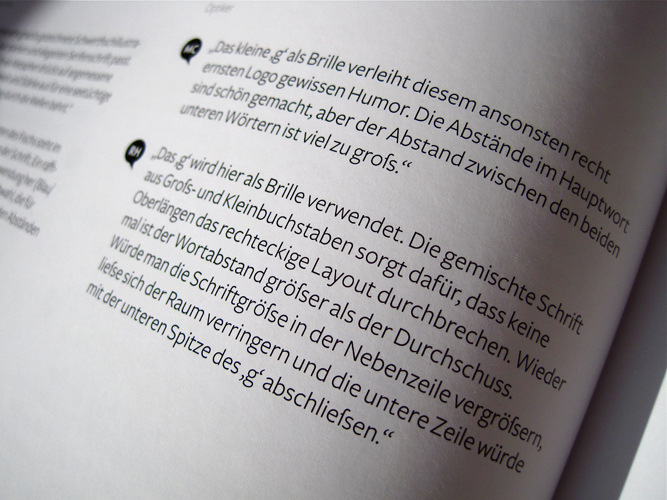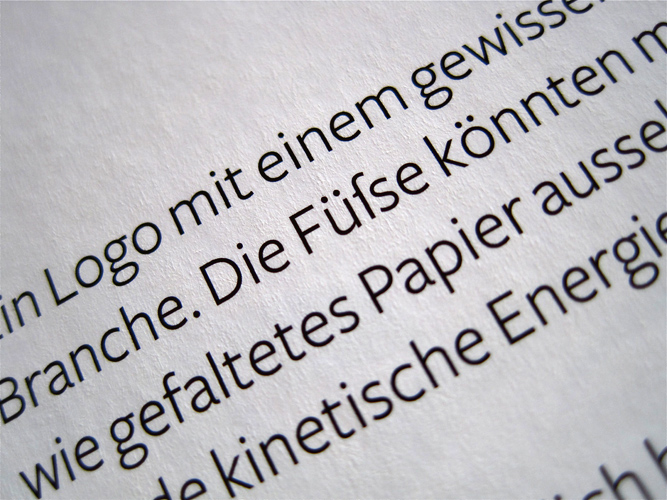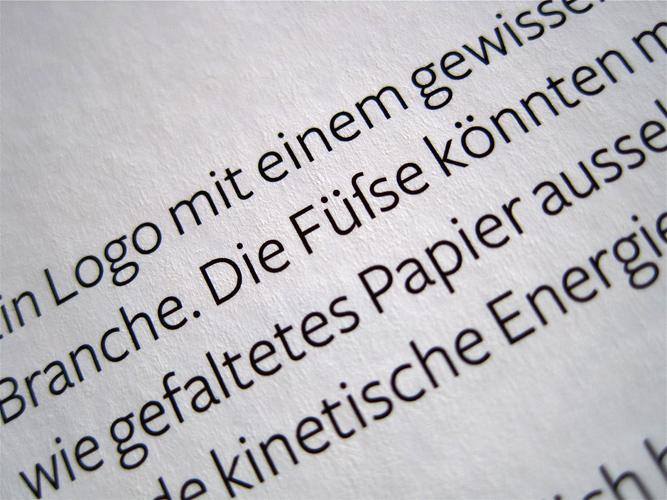
Dieses Buch treibt mich in den Wahnsinn!
Jedes Mal, wenn ich dieses Buch in die Hand nehme, bekomme ich schlechte Laune*! Und es wird nicht besser. Ich habe das Buch schon lange, allein: An dieses ß-Konstrukt gewöhne ich mich nicht. Ich stolpere darüber, bei jeder einzelnen Anwendung. Ich verlese mich, es ärgert mich. Wenn Typografie der Dienst am Leser ist, dann hat das Buch diesen Zweck nicht erfüllt. :grummel:  :bandit:
Geht es Euch auch so oder pflege ich da eine Einzelantipathie?
* Und das liegt nicht nur an den mitunter schwer erträglichen Plattitüden, die die bewertenden Gestalter da vom Stapel lassen. Und dem inflationär verwendeten Begriff »konzeptuell«. Und dazu die teilweise sehr seltsamen Bewertungen … Auch lassen mich einige merkwürdige Formulierungen vermuten, dass die Übersetzung der englischen Originaltexte an manchen Stellen nicht ganz gelungen ist …
Sagen wir mal so: Wenn die ß-resistenten Schweizer das verzapft hätten, könnte man sagen: Besser als ss ist es allemal, also ein kleiner Schritt in die richtige Richtung. Wenn das aber, wie zu argwöhnen ist, als ß-Substitut gedacht ist, dann ist es einfach unerträglich und Deine schlechte Laune ist berechtigt.
Jessasmariundjosef, da steht derart überhebliches Geschwurbel drin, dass ich gar nicht weiter reinschauen möchte. Margo Chase hat sich mit ihrer "erste Wahl" und den Aussagen zur Nicht-Berücksichtigung der Reproduktion so derart selbst ins Knie geschossen, dass ich das nicht wirklich ernst nehmen kann.
Ma abgesehen von der Möchtegern-Schrift: Schaut her, wie toll ich bin.
Ja bertel, Du hast vollkommen recht! Die Kommentare, die dort zu den Logos stehen, sind zwar in manchen Fällen interessant, in vielen Fällen aber bloße Beschreibungen dessen, was man ohnehin sieht und in überraschend vielen Fällen sind die Kommentare inhaltlich sehr oberflächlich und kurz gedacht (oder auch gar nicht mal so schlau). Bei etlichen ausgelobten Favoriten habe ich mir wirklich die Augen gerieben und mich gefragt, ob die Differenz in der Wahrnehmung rein vom unterschiedlichen kulturellen Hintergrund herrührt, oder wie das zustande kommt. Es kann natürlich auch sein, dass ich eine völlig falsche Wahrnehmung habe und die vier Kommentatoren im Buch recht haben ;-).
Aber gerade Margo Chase scheint eine immense Vorliebe für handgezeichnete Logos zu haben und klopft die Entwürfe fast nur darauf ab: handgezeichnet - gut, alles andere - nicht so gut. Erstaunlich ist auch, wie unterschiedlich die Vier den Versalienausgleich und andere Details in den Logos bewerten. Das hat schon einen gewissen Unterhaltungswert und man sieht zumindest, dass anderswo auch nur mit Wasser gekocht wird. Aber ich glaube, wenn das Buch wirklich ein fachlich versierter Ratgeber in der Bewertung von Logos sein möchte, der Anfängern (und Fortgeschrittenen) die sorgfältige und durchdachte Gestaltung von Logos nahebringen soll, dann wäre es sinnvoller gewesen, vorab einige Qualitätsmerkmale und Bewertungsparameter zu definieren, anhand derer die Betrachter die Logos dann einordnen, als diese eitle Dampfplauderei abzudrucken. Klar, ich weiß schon, dass solche Buchkonzepte immer heikel sind und es ist auch immer einfach, sich nachträglich hinzustellen und die Aussagen anderer zu bemängeln. Andererseits kostet das Buch ein ganze Menge Geld und beansprucht für sich, »wirklich gute Logos zu erklären«. Und daran müssen sich die Autoren dann auch messen lassen. Und dann noch dieses »fs« … :-|
PS: Dabei gefällt mir die Schrift ansonsten gut. Und wenn sie sogar ein brauchbares ß enthält, dann ärgert mich der Buchstabenhumbug umso mehr!
Ungewohnt? Ja. Aber es scheint eine Tradition der Setzer zu geben, die das ß für eine Lang-s/s-Ligatur halten, habe schon häufiger solcherlei Bücher gelesen, die aber vor 1900 gedruckt wurden. Nach ein paar Seiten gewöhnt man sich daran schon. Was aber besonders irritierend ist, ist der Nichtgebrauch des Lang-s. Wenn man sich schon derlei Traditionen bedient, sollte man das auch konsequent machen.
Jenseits allem finde ich die Schrift, öh, luftig und wenn das Lang-s benutzt würde, vielleicht sogar spannend.
Gut möglich, dass das eine alte Tradition ist. Ich habe es aber wirklich nicht geschafft, mich daran zu gewöhnen. Ich habe das Buch so gut wie durchgelesen - und es macht mich nach wie vor irre. Ich verstehe nicht, warum man in diesem Buch ohne Not (Stefan schreibt ja, dass diese Schrift über ein reguläres ß verfügt) eine solche Lesestolperfalle eingebaut hat. Ich empfinde das als reine Eitelkeit des Buchgestalters - und mehr als überflüssig.
Wenn dan mal wenigstens das ſs an den Stellen verwendet woirden wäre, wo es hin passt, also z.B. bei daſs und anderen Worten, die auf ss enden, sonst hätte man oft besser zu ſſ gegriffen, und auch sonst ſ regelgerecht verwendet, das wär doch mal was, statt als ſs Ersatz für ß. Auch könnte dies bei Worten wie Fluſsſchifffahrt sogar sehr nützlich sein. in meinen Schriften ist daher auch ſs als Ligatur enthalten, aber eben nicht als ß-Alternative.
Aber es scheint eine Tradition der Setzer zu geben, die das ß für eine Lang-s/s-Ligatur halten, habe schon häufiger solcherlei Bücher gelesen, die aber vor 1900 gedruckt wurden. Nach ein paar Seiten gewöhnt man sich daran schon. Was aber besonders irritierend ist, ist der Nichtgebrauch des Lang-s. Wenn man sich schon derlei Traditionen bedient, sollte man das auch konsequent machen.
Diese Tradition hat es wirklich gegeben, will sagen, ausschliesslicher Gebrauch von ſs, während sonst kein ſ mehr verwendet wird. So gesehen ist es ein historischer Gebrauch, der hier nachgemacht wird. Allerdings kann das keine Ausrede sein. Es hat diesen Gebrauch zwar wirklich gegeben, doch heutzutage verstösst er gegen jede Lesegewohnheit. Unmotivierte Historizität um ihrer selbst willen.
Auch in anderen typografischen Aspekten sind die Discworld Novels sehr spannend, da der Tod (er ist dort ein anthropomorphes Wesen) spricht nur in Kapitälchen und ohne Anführungszeichen. Die Auditors, eine Art von übernatürlichen Wesen, reden auch ohne Anführungszeichen und im ganz normaler gemischter Schreibweise.
Daher finde ich die Typografie in diesen Büchern sehr interessant, weil sie den Charakteren noch mehr Leben und Identität geben, als die beschreibenden Wörter.
Ich bin abgeschweift; Ich kann deine Anthipatie gegen dieses Buch verstehen ;)